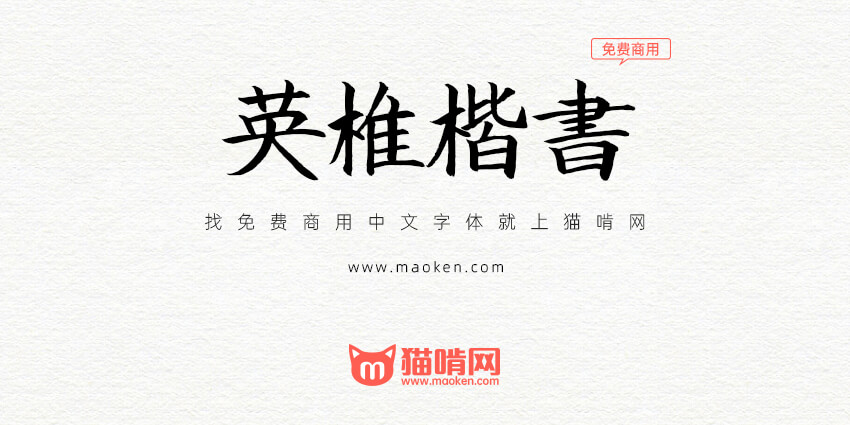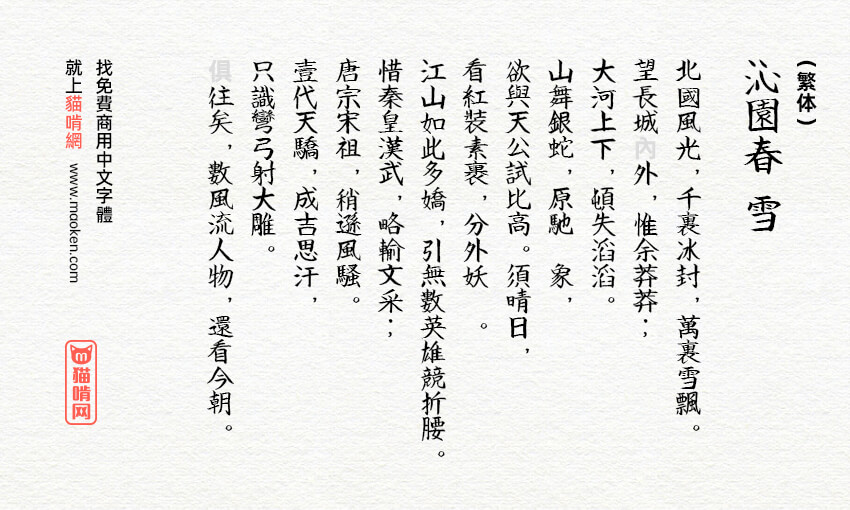
英椎楷书:书写十分工整漂亮的日系手写字体免费商用
英椎楷书是日本acfont自己手写开发的一款字体,这款字体端庄雄伟,书写工整,是一款十分好看的手写字体。英椎楷书共收录了6879个文字,因为日文字符一般是以JIS水准为标准,所以繁体字支持得比较完整。简体字数相对较少,不过也确实是一款难得的字体。喜欢的朋友赶紧下载吧!